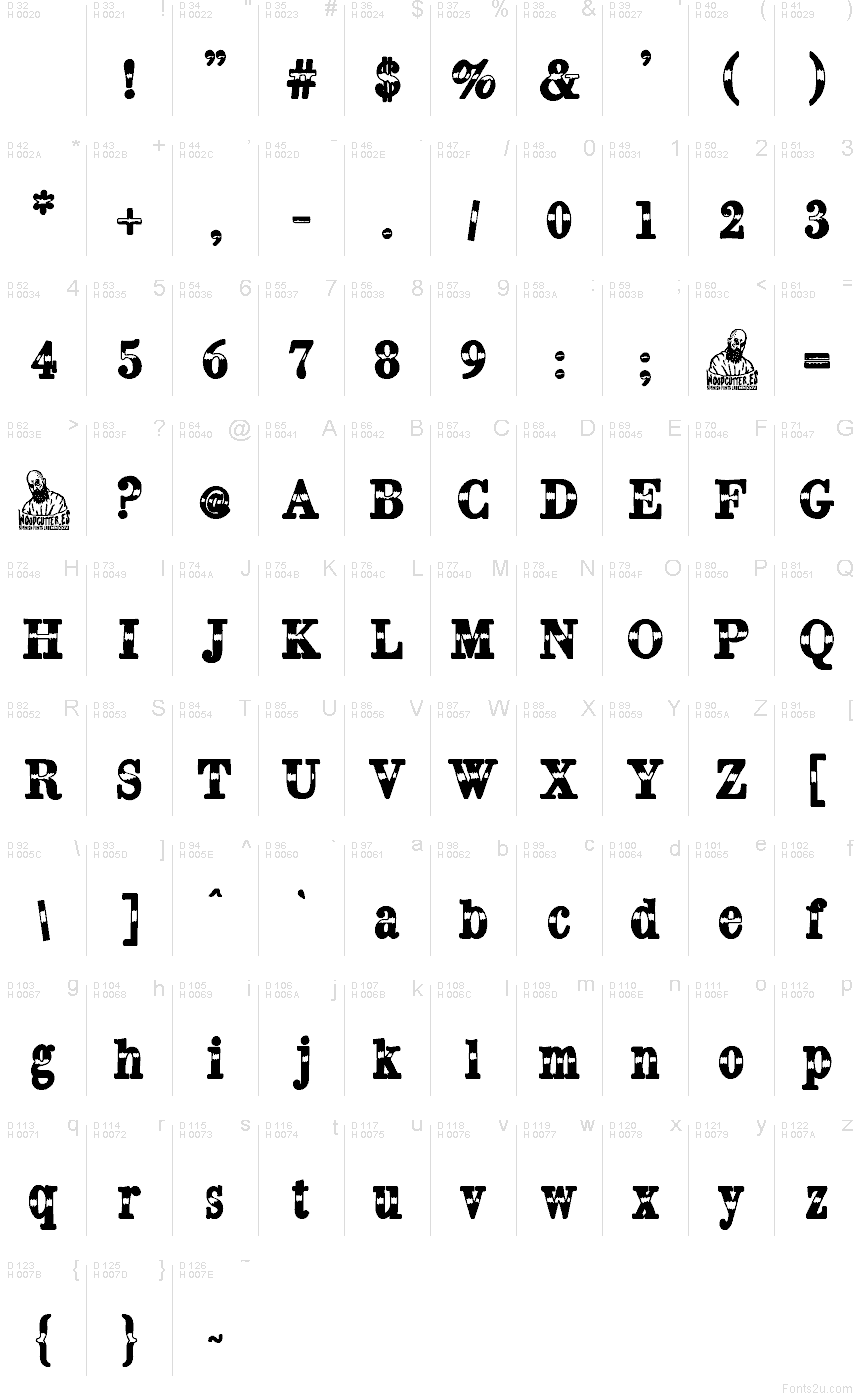
Nevermore Land est une police display gratuite signée Woodcutter Manero, inspirée des affiches de films d'horreur rétro. Ses empattements massifs sont traversés par des entailles irrégulières qui rappellent une usure prononcée. Le résultat est résolument théâtral plutôt que simplement vieilli, offrant une silhouette imposante aux bords irréguliers pour une ambiance gothique digne d'un conte de fées.
Idéale pour des titres d'affiches, des graphismes d'Halloween, la signalétique d'attractions hantées, des couvertures de livres ou des packagings sombres où l'atmosphère est primordiale. Utilisez-la pour des titres courts ou des lettrines : ses lignes lacérées et ses formes robustes donnent aux mots une présence scénique inquiétante.